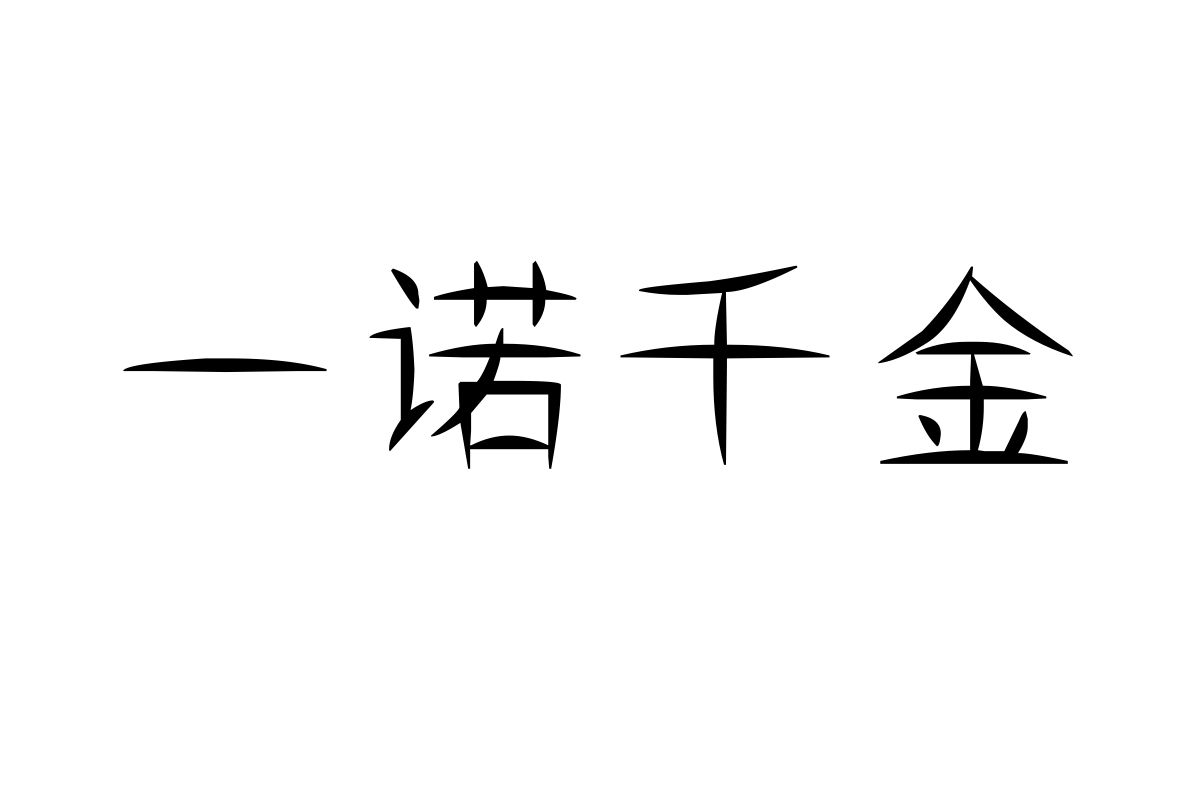
汉标赵都体是一种书法字体,源自中国汉代的书写风格。这种字体的特点是笔画流畅,结构紧凑,线条粗细适中,具有很高的艺术价值和实用价值。
汉标赵都体的笔画特点是:笔画圆润,线条流畅,转折自然。这种字体的字形结构紧凑,线条粗细适中,既有力量感又不失柔美。它的笔画粗细变化丰富,既有粗犷豪放的一面,又有细腻婉约的一面,给人以强烈的视觉冲击力。
汉标赵都体的书法风格特点:线条流畅,结构紧凑,笔画圆润,粗细适中。这种字体的书写速度较快,适合用于各种场合的书写,如书信、公文、诗词等。同时,由于其线条流畅,结构紧凑,笔画圆润的特点,使得汉标赵都体在书法作品中具有很强的美感和艺术性。
总的来说,汉标赵都体是一种非常有特色的书法字体,它既保留了汉代书法的精髓,又融入了现代审美的需求,是书法艺术中不可多得的艺术珍品。